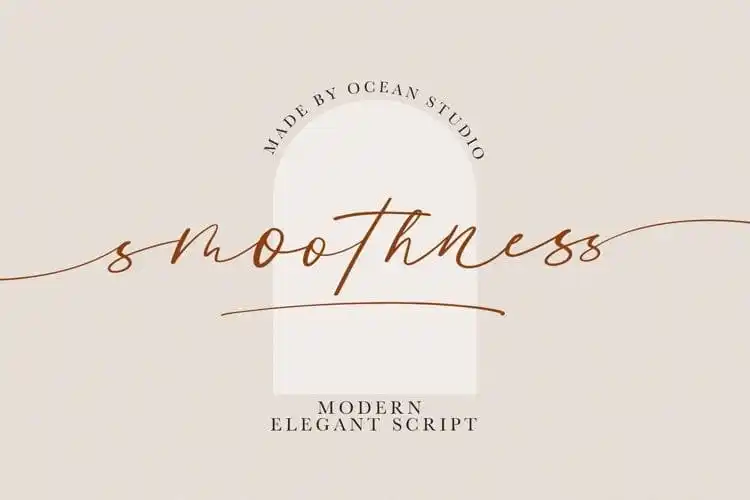
Smoothness Script Font – Download Grátis
A Smoothness Script Font é uma elegante e luxuosa tipografia script que oferece um toque sofisticado aos seus projetos digitais. Criada pela Ocean Studio, esta fonte não apenas proporciona uma experiência visual única e fluida, mas também destaca-se por seu suporte multilíngue completo. Ideal para diversas aplicações como anúncios, branding, logotipos, embalagens, títulos e headlines em design editorial, a Smoothness Script Font se torna um recurso indispensável para designers que buscam expressar seus ideais criativos de maneira sofisticada e profissional. Com seu estilo fluido e orgânico, essa fonte não só adorna suas criações, mas também as dá um toque de elegância que vai muito além do básico.